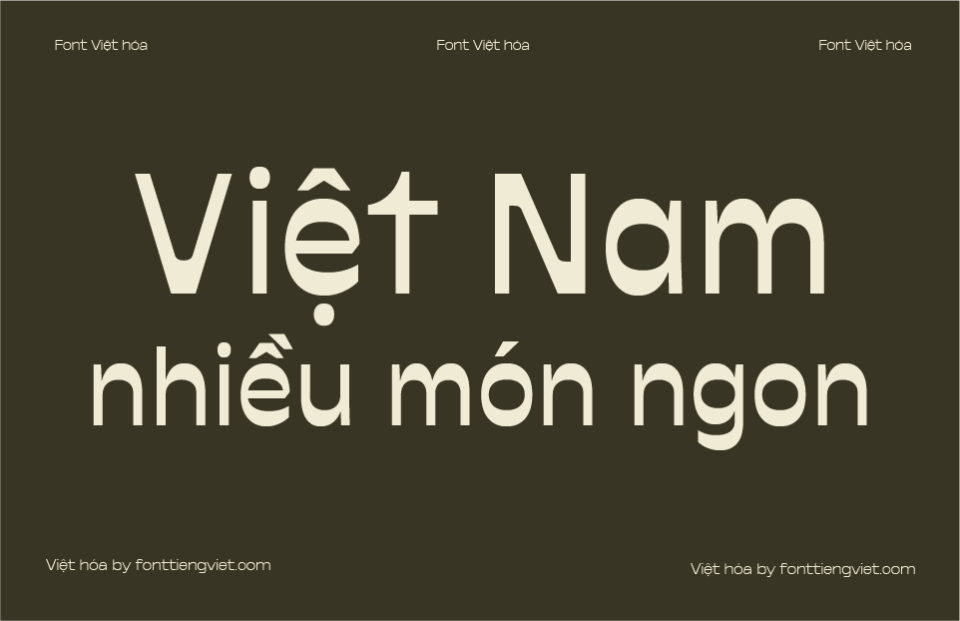
Font Việt hóa 1FTV VIP Antipol Medium
Giới thiệu về bộ Font Việt hóa 1FTV VIP Antipol Medium
Trong thế giới đồ họa hiện đại, việc lựa chọn một bộ Font Miễn Phí chất lượng đóng vai trò quyết định đến sự thành công của một sản phẩm truyền thông. Font Việt hóa 1FTV VIP Antipol Medium nổi lên như một giải pháp hoàn hảo cho những nhà thiết kế đang tìm kiếm sự cân bằng giữa nét cổ điển và hơi thở đương đại. Đây là phiên bản được tinh chỉnh kỹ lưỡng, hỗ trợ đầy đủ bộ gõ tiếng Việt với các dấu thanh được đặt chuẩn xác, giúp người dùng không còn lo lắng về lỗi hiển thị khi soạn thảo văn bản. Với độ dày trung bình (Medium), font chữ này mang lại cảm giác vững chãi nhưng không quá nặng nề, phù hợp cho nhiều mục đích sử dụng khác nhau từ in ấn đến hiển thị kỹ thuật số.
Đặc điểm nổi bật của Font Việt hóa 1FTV VIP Antipol Medium
Thiết kế hình học tinh tế
Font Việt hóa 1FTV VIP Antipol Medium sở hữu cấu trúc hình học đặc trưng với các đường nét dứt khoát và tỉ lệ cân đối. Sự đồng nhất trong khoảng cách giữa các chữ cái giúp văn bản trở nên dễ đọc, ngay cả khi hiển thị ở kích thước nhỏ. Đặc biệt, các góc bo tròn nhẹ nhàng tạo nên vẻ ngoài thân thiện, hiện đại, rất thích hợp cho các dự án thiết kế thương hiệu hoặc trình bày nội dung trên trang web học tập. Sự linh hoạt này cho phép các bạn học sinh và giáo viên dễ dàng ứng dụng vào việc làm slide bài giảng hoặc thiết kế báo tường sinh động.
Khả năng ứng dụng đa dạng
Không chỉ dừng lại ở các thiết kế đồ họa cao cấp, Font Việt hóa 1FTV VIP Antipol Medium còn là lựa chọn ưu tiên cho các tiêu đề bài viết, bìa sách hoặc biểu ngữ sự kiện. Nhờ tính thẩm mỹ cao, font chữ này giúp nâng tầm giá trị hình ảnh cho bất kỳ dự án nào. Bạn có thể sử dụng nó để tạo điểm nhấn cho các poster quảng cáo, làm nổi bật thông tin quan trọng mà vẫn giữ được sự tinh tế, lịch sự. Khả năng tương thích tốt trên các phần mềm thiết kế phổ biến như Photoshop, Illustrator hay Canva cũng là một điểm cộng lớn khiến bộ font này được săn đón.
Lưu ý khi sử dụng Font Việt hóa 1FTV VIP Antipol Medium
Quy tắc kết hợp font chữ
Để đạt hiệu quả thị giác tốt nhất, bạn nên kết hợp Font Việt hóa 1FTV VIP Antipol Medium với các font không chân (Sans Serif) thanh mảnh hoặc các font có chân (Serif) truyền thống để tạo sự tương phản. Khi dùng cho tiêu đề chính, hãy để kích thước chữ lớn và khoảng cách dòng thoáng đãng nhằm tạo không gian nghỉ cho mắt người xem. Việc sử dụng màu sắc tối giản như đen, trắng hoặc các tông màu pastel cũng sẽ làm tôn lên vẻ đẹp nguyên bản của bộ chữ này, giúp thông điệp của bạn được truyền tải một cách rõ ràng và chuyên nghiệp nhất có thể.
Kết luận về bộ Font Việt hóa 1FTV VIP Antipol Medium
Tóm lại, Font Việt hóa 1FTV VIP Antipol Medium là một công cụ hỗ trợ đắc lực cho cộng đồng sáng tạo tại Việt Nam. Với thiết kế hiện đại, khả năng hiển thị tiếng Việt hoàn hảo và tính ứng dụng cao, đây chắc chắn là cái tên không thể thiếu trong bộ sưu tập tài nguyên thiết kế của bạn. Hãy trải nghiệm ngay sự khác biệt mà bộ font này mang lại để tạo nên những tác phẩm ấn tượng và độc đáo nhất. Đừng quên truy cập vào Font Miễn Phí, Font Việt Hóa, Font Việt hóa 1FTV VIP Antipol Medium để cập nhật thêm nhiều bộ chữ đẹp mắt và chất lượng phục vụ cho công việc thiết kế hàng ngày của mình.